أفضل 36 خطًا للآلة الكاتبة ️ 2023
نشرت: 2023-05-14هل أنت مصمم جرافيك تبحث عن الخط المثالي للآلة الكاتبة لإضافة لمسة كلاسيكية إلى تصميماتك؟ أو ربما كنت فقط من عشاق الطباعة وتبحث عن بعض الإلهام؟ في كلتا الحالتين ، لقد أتيت إلى المكان الصحيح!
في هذه المقالة ، سنشارك معك أفضل اختياراتنا من أفضل 36 خطًا للآلة الكاتبة المتاحة للتنزيل. هذه الخطوط مثالية لإضافة مظهر "المدرسة القديمة" إلى تصميماتك وستجعل بالتأكيد عملك متميزًا عن البقية.
سواء كنت تعمل في مشروع للعلامة التجارية أو تصمم ملصق أو تنشئ دعوة ، فإن خطوط الآلة الكاتبة هذه ستضيف لمسة فريدة إلى تصميماتك وتجذب انتباه جمهورك. لذلك ، دون مزيد من اللغط ، دعنا نتعمق في عالم خطوط الآلة الكاتبة ونرى ما لديهم لتقدمه!
أفضل الخطوط المميزة للآلة الكاتبة
هل تبحث عن خطوط آلة كاتبة عالية الجودة لمشاريع التصميم الخاصة بك؟ تحقق من اختيارنا لأفضل الخيارات المتميزة المتاحة ، كل واحدة مصممة بعناية لمساعدتك في الحصول على المظهر الكلاسيكي المثالي. ألق نظرة فاحصة على هذه الخطوط واكتشف أيها مناسب لمشروعك.
الآلة الكاتبة القديمة
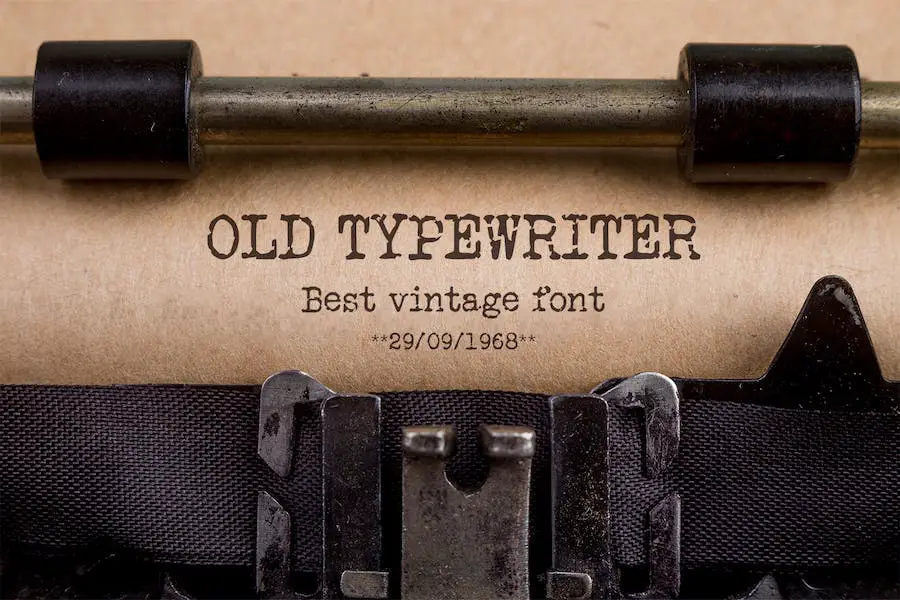
Old Typewriter هو خط آلة كاتبة يعيد سحر الكتابة الميكانيكية في تصميماتك. يضيف أسلوبها المصنوع من الألواح الرقيقة لمسة من الرجعية إلى إبداعاتك ، مما يجعلها مثالية لأولئك الذين يحبون المظهر الكلاسيكي.
هذا الخط متعدد الاستخدامات ويمكن استخدامه في مشاريع مختلفة مثل الصحف والملصقات والقمصان وفنون الجدران والمزيد.
بفضل تصميمها الموضوعي ، يمكن للآلة الكاتبة القديمة أن تجعل عناوينك بارزة وتضيف طابعًا إلى تخطيطات مجلاتك.
كما أن المظهر الفريد للخط يجعله اختيارًا ممتازًا لإنشاء تصميمات متعلقة بالطب الشرعي أو مسرح الجريمة. إنه خط من المؤكد أنه يجذب الانتباه ويجعل عملك متميزًا.
من خلال تصميمها الموضوعي ، تعد خطوط الآلة الكاتبة هي الأفضل للتصميم ويمكن أن تجعل عناوينك تنبثق وتضيف طابعًا إلى تخطيطات مجلاتك.
آلة كاتبة إنجما
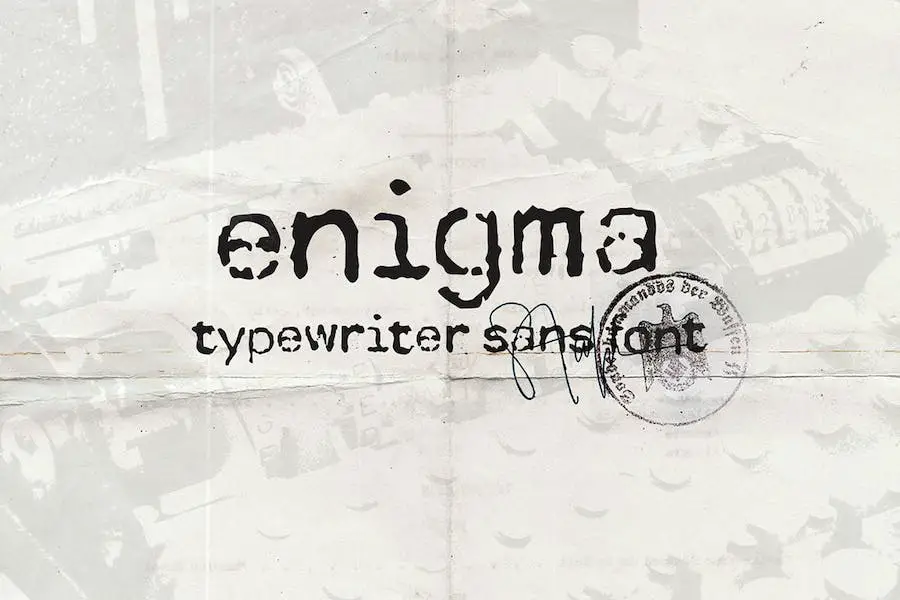
Enigma Typewriter هو خط يمكن أن يعيدك إلى الأيام الخوالي ، ويعيد إنشاء المستندات والأوراق القديمة بسهولة.
مستوحى من آلة Enigma German ، يأتي هذا الخط في ملف ttf واحد ، والذي يدعم الحروف الرسومية متعددة اللغات.
إذا كنت تبحث عن خط آلة كاتبة لإضافته إلى مشروع التصميم الخاص بك ، فقد يكون من المفيد التفكير في Enigma Typewriter.
بفضل طابعها العتيق ، يمكن أن تضفي على تصميمك طابع المدرسة القديمة الذي سيجذب انتباه الناس بالتأكيد. يعد Adobe Typewriter Font هذا مثاليًا للمصممين الذين يرغبون في تجربة أنماط طباعة مختلفة وإنشاء تصميمات فريدة.
كاتالينا آلة كاتبة
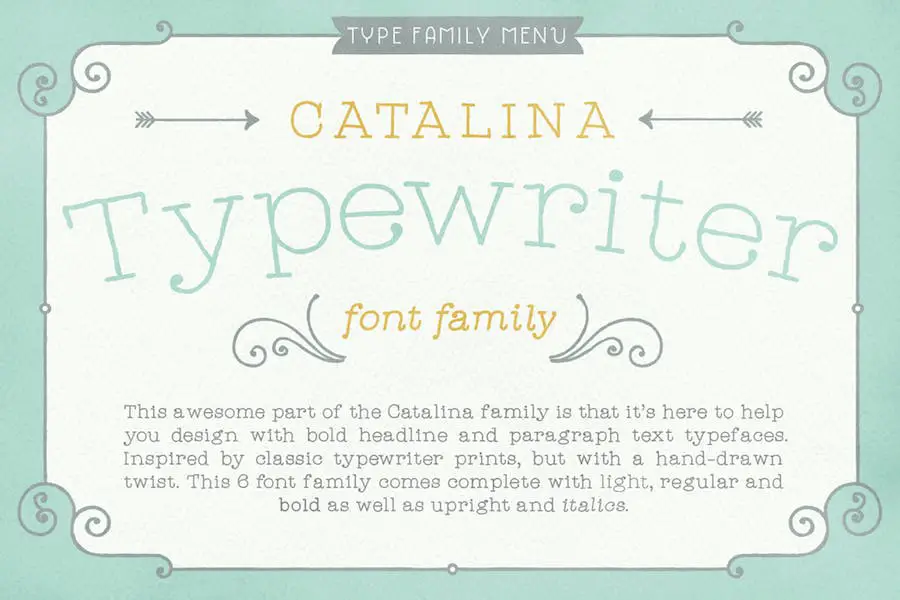
Catalina Typewriter هو خط يمكنه إضافة شخصية وشخصية لأي مشروع ، خاصة تلك المتعلقة بالموضوعات القديمة أو القديمة.
يأتي هذا الخط بثلاثة أوزان وأنماط مختلفة: sans و slab serif ، مما يمنح المصممين المزيد من الخيارات للاختيار من بينها.
لمصممي الجرافيك الذين يتطلعون إلى تحسين مشاريعهم على Canva ، يعد خط الآلة الكاتبة هذا خيارًا رائعًا لتحقيق مظهر بنمط الآلة الكاتبة.
وقع الآلة الكاتبة
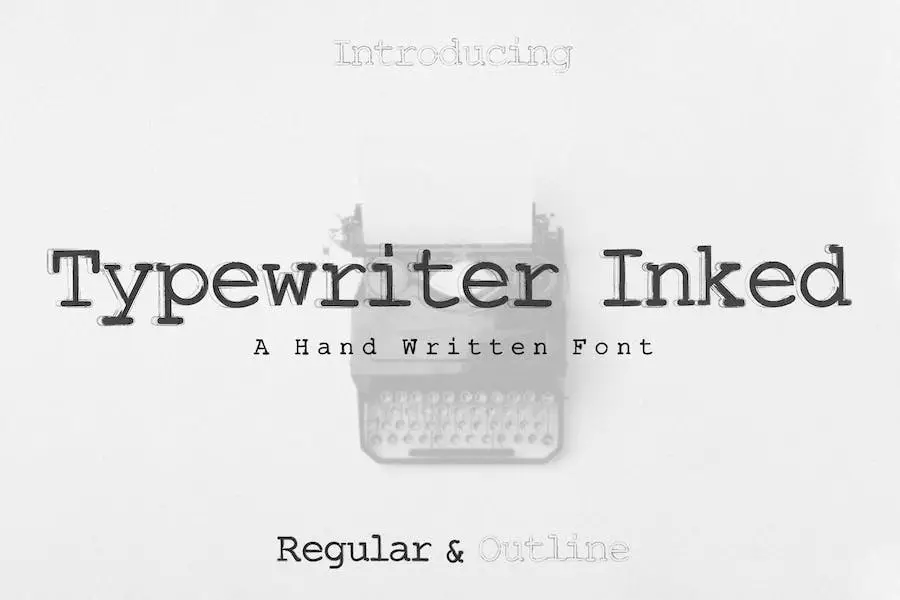
يعتبر الخط Typewriter Inked هو الخيار الأمثل لمصممي الجرافيك الذين يبحثون عن خط أنيق وفريد من نوعه للارتقاء بمشاريع التصميم الخاصة بهم.
يتألف هذا الخط من أحرف كبيرة وصغيرة وأرقام وعلامات ترقيم ورموز ، مما يجعله خيارًا متعدد الاستخدامات بشكل لا يصدق لاحتياجات التصميم المختلفة.
بأسلوبه الفاخر والواثق ، يعد هذا الخط مثاليًا لإنشاء تصميمات التغليف والعروض التقديمية والشعارات والعناوين الرئيسية والملصقات والعلامات التجارية والاقتباسات والعناوين وعناوين المجلات وتخطيطات الويب والإعلانات والدعوات وتصميم العبوات والكتب وأي تصميم إبداعي تقريبًا .
إذا كنت مصممًا يعمل على Figma ، فإن خط Typewriter Inked هو خيار ممتاز. بشخصياته الجريئة والقوية ، سيساعد هذا الخط تصميماتك على التميز ، مما يمنحها لمسة من الأناقة الكلاسيكية.
ريمنجتون الحرير
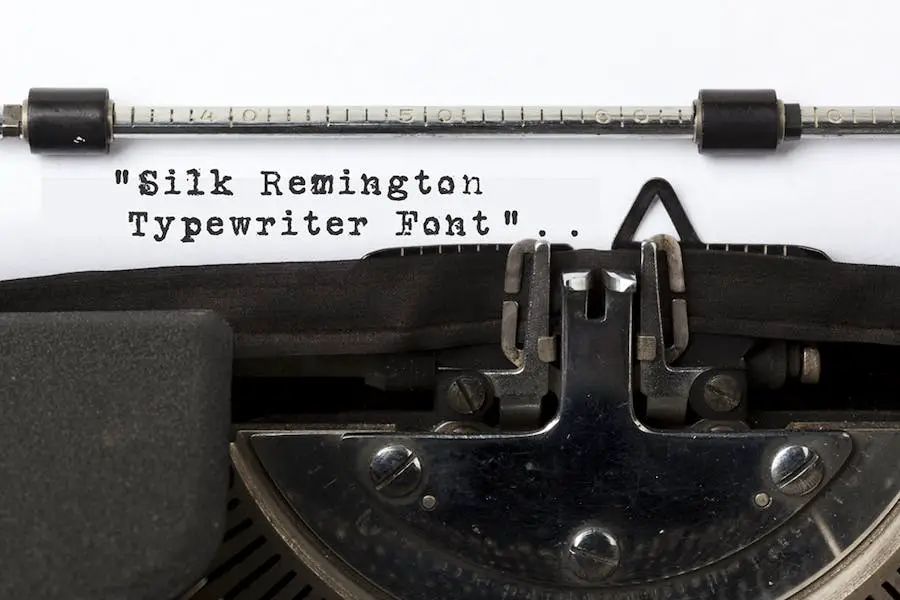
Silk Remington هو خط آلة كاتبة جديد تم تطويره بواسطة Jadugar Design Studio. تم تصميم خط الآلة الكاتبة الحديث هذا لتوفير إحساس واقعي بآلة كاتبة قديمة ، مما يمنح مشاريعك لمسة عتيقة.
يأتي Silk Remington في سبعة أنماط مختلفة ، بما في ذلك Thin و Regular و Rough Regular و SemiBold و Rough-SemiBold و Bold و Rough Bold.
كاتب
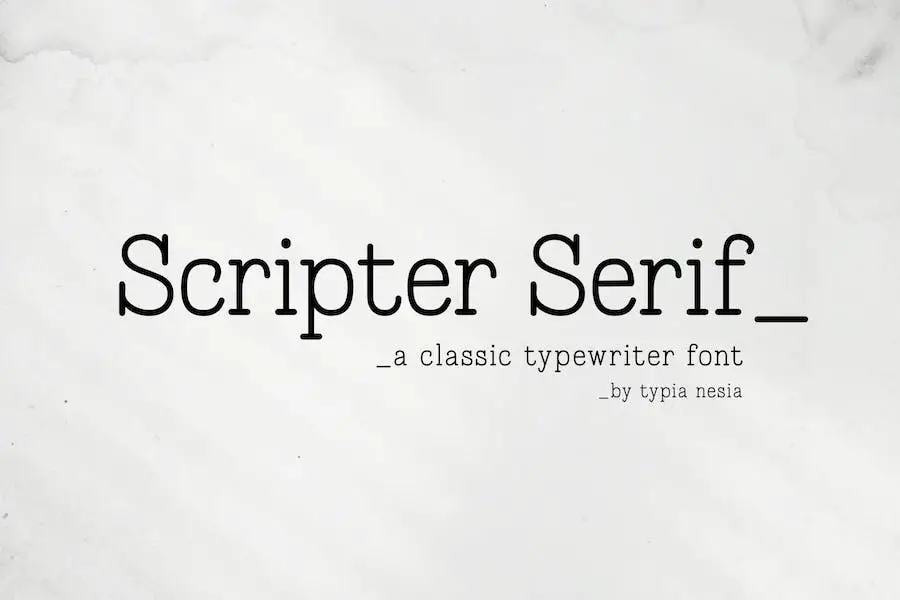
Scripter هو خط آلة كاتبة يمكن استخدامه في العديد من المشاريع ، من الشعارات الكلاسيكية والعلامات التجارية إلى تصميم المجلات. Scripter هو خط آلة كاتبة مثالي لأولئك الذين يرغبون في إضافة إحساس بالحنين إلى تصميماتهم.
يقدم هذا الخط تصميمًا تحريريًا كلاسيكيًا يناسب المواد الترويجية للأزياء والعلامة التجارية لمخطط الزفاف وتصميم القرطاسية. يعد Scripter أيضًا ممتازًا لتصميم المدونات وتصميم الإعلانات ودعوات بطاقات الزفاف والاقتباسات الفنية وديكور المنزل وعناوين غلاف الكتب / الروايات والمناسبات الخاصة.
ليس نوعي
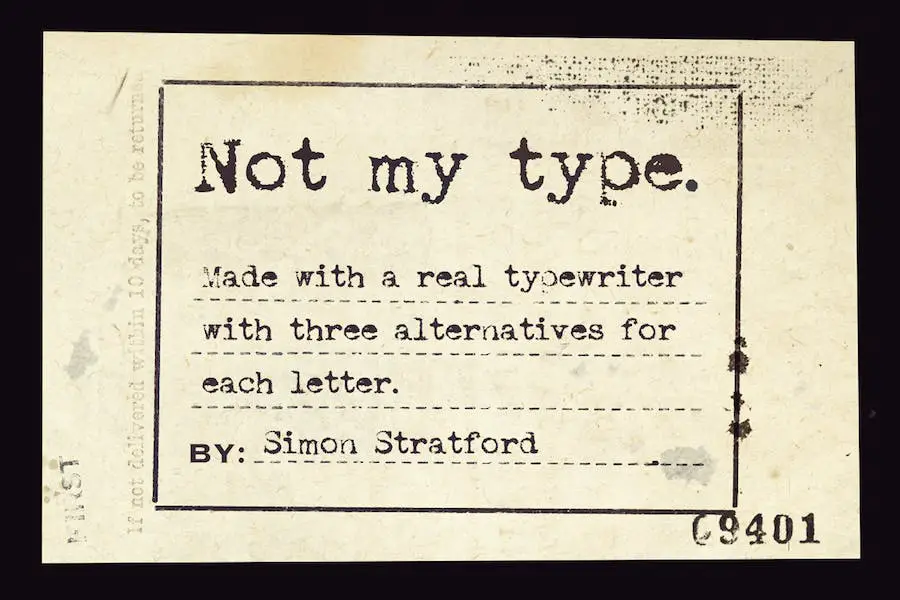
Not My Type هو خط يمكنه تحسين مشاريع التصميم الخاصة بك بمظهره الفريد والأنيق.
يأتي هذا الخط بنمط واحد يتضمن أحرفًا كبيرة وصغيرة ، إلى جانب ثلاثة بدائل لكل منها ، مما يوفر لك الكثير من الخيارات للاختيار من بينها.
ميرشانت ليدجر
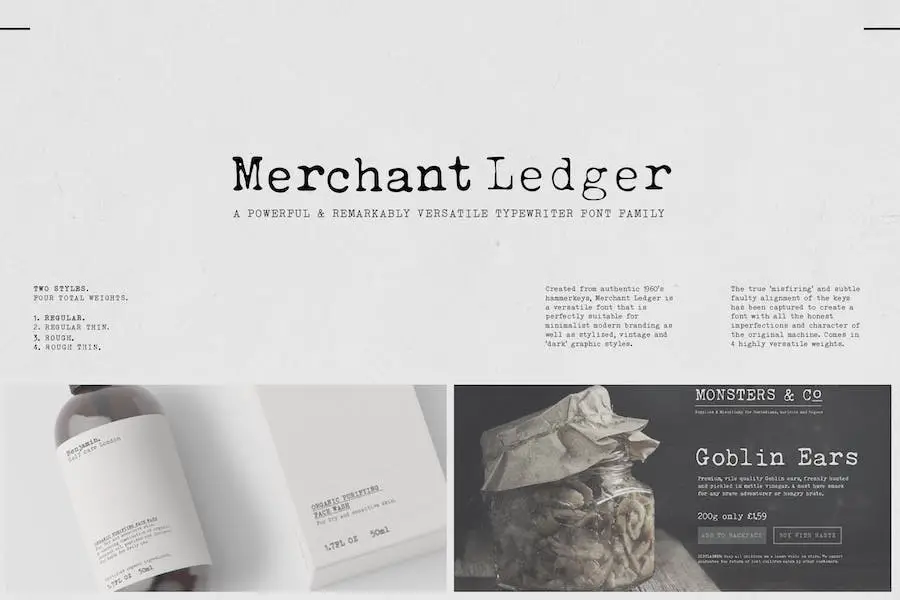
Merchant Ledger هي عائلة خطوط متعددة الاستخدامات بشكل لا يصدق يمكن استخدامها لمجموعة من التصميمات. سواء تم استخدامه للعلامات التجارية البسيطة والحديثة أو الملصقات الجريئة ، يمكن لخط الآلة الكاتبة هذا تقديم ما تحتاجه.
تايبريتر
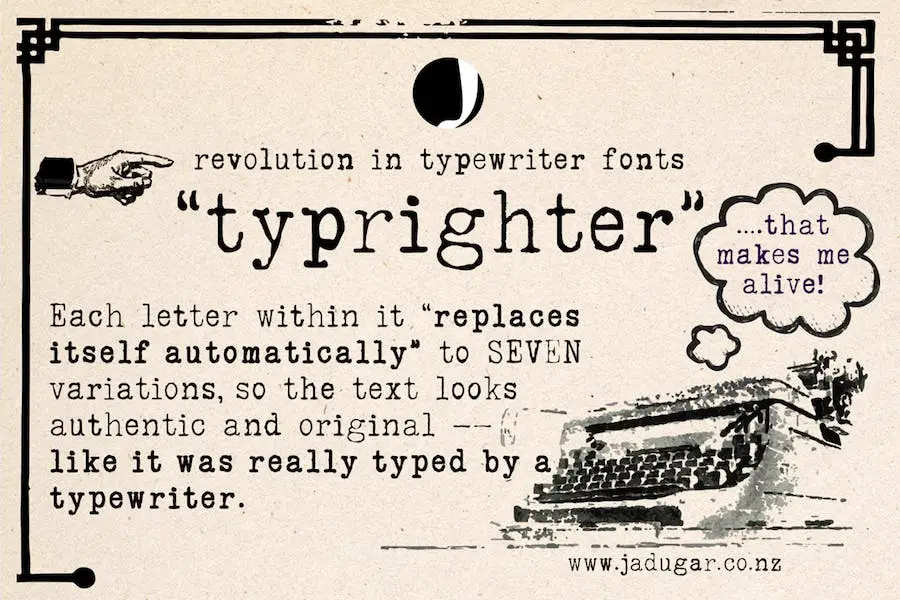
Typrighter هو خط يعد بجلب تجربة الآلة الكاتبة الحقيقية إلى جهاز الكمبيوتر الخاص بك. استخدم صانعو هذا الخط ميزة البدائل السياقية التطبيقية في Fontlab لإنشاء ستة أشكال مختلفة لكل حرف من الأبجدية الإنجليزية القياسية.
فوضى في Keytic
Mess in Keytic هو خط كلاسيكي مستوحى من جماليات حروف الآلة الكاتبة. يمكن استخدام هذا الخط لإنشاء فقرات أو نص ، بالإضافة إلى صياغة العناوين على أغلفة المجلات أو العناوين الرئيسية في الصحف.
رونس
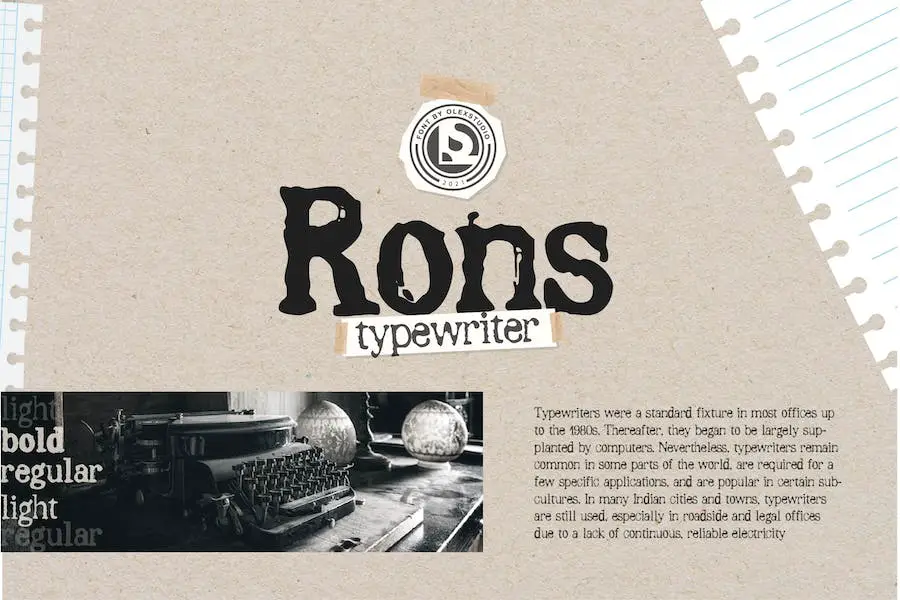
Rons Typewriter هو خط Serif مذهل يمكنه إضافة الأناقة والأناقة إلى جميع مشاريع التصميم الخاصة بك. يتميز هذا الخط الجميل بأحرف قياسية ، بما في ذلك الأحرف الصغيرة والكبيرة والأرقام وعلامات الترقيم والحروف الرسومية الدولية.
أفكار مثالية
أفكار مثالية هو خط آلة كاتبة رائع وممتع يأتي بثلاثة أشكال مختلفة. يتضمن الإصدار الأول علامات ختم أصلية مصنوعة بالحبر ، مما يوفر إحساسًا فريدًا وعتيقًا لتصميماتك.
الشكل الثاني له مظهر أكثر استقامة وخطورة ، مما يجعله مثاليًا للمشاريع الاحترافية. أخيرًا ، يتميز الخط الثالث بخط أساس غير منتظم ، مما يضيف لمسة غير تقليدية ومرحة إلى أي تصميم.
إعادة الكتابة
Retrotype هو خط مصمم لإضفاء القليل من الحنين إلى التصميم الحديث. إنه خط ممتع وكلاسيكي ومركب ومباشر يمكنه إضافة شخصية إلى أي مشروع. مستوحاة من الآلات الكاتبة الخالدة القديمة ، تم رقمنة Retrotype لعالم اليوم.
يأتي خط الآلة الكاتبة من Google مع العديد من الميزات التي تجعله متميزًا. إحدى السمات الجديرة بالملاحظة هي بساطته.
المحقق
Detective هو خط آلة كاتبة فريد يجمع بين سحر الطراز القديم وحساسيات العصر الحديث.
يشيد هذا الخط المصنوع يدويًا بالاختراع الكلاسيكي للآلة الكاتبة ، التي غيرت عادات القراءة وجعلت الوضوح في المقدمة.
باستخدام المحقق ، يمكنك إضافة لمسة شخصية قديمة إلى مراسلات عملك أو أي عمل آخر يتطلب مظهرًا رجعيًا.
يعد خط الآلة الكاتبة Detective خيارًا ممتازًا لمن يبحثون عن "Typewriter Fonts for Word".
آلة كاتبة
TYPEWRITER هو خط محرف عتيق مثالي لمصممي الجرافيك الذين يرغبون في إضافة لمسة من الحنين إلى مشاريعهم.
هذا الخط مستوحى من متاجر التحف والآلة الكاتبة القديمة ليسوع ، مما يجعله إضافة فريدة لمجموعة خطوط أي مصمم.
إذا كنت تبحث عن خط يمنح مشروعك طابعًا رجعيًا ، فإن TYPEWRITER يستحق بالتأكيد التفكير فيه.
بفضل الحروف المصممة بعناية والاهتمام بالتفاصيل ، فهي الخيار الأمثل لأي شخص يبحث عن خطوط الآلة الكاتبة لـ Circuit.
اكتب الكاتب القديم
يعد خط Type Old Writer خيارًا أنيقًا وفريدًا لمصممي الرسوم الذين يبحثون عن خط الآلة الكاتبة المثالي لرفع مشروعات التصميم الخاصة بهم.
يجسد هذا الخط ، بمظهره الكلاسيكي ، جوهر الكتابة القديمة بمظهرها المتميز والأصيل.
إحدى الميزات البارزة لـ Type Old Writer هي تنوعها. إنه يعمل بشكل جيد في مجموعة متنوعة من السياقات ، من تصميمات الطباعة مثل الملصقات والنشرات إلى التصميمات الرقمية مثل مواقع الويب وتطبيقات الأجهزة المحمولة.
بالإضافة إلى ذلك ، يمكنك استخدام خطوط الآلة الكاتبة لتصميمات الوشم ، مما يجعلها خيارًا رائعًا لأولئك الذين يتطلعون إلى إنشاء فن جسم مستوحى من الآلة الكاتبة.
خط الآلة الكاتبة
خط الآلة الكاتبة هو الخط المثالي للمصممين الذين يرغبون في تحقيق إحساس قديم وعتيق في تصميماتهم.
هذا الخط هو الأنسب للملصقات والمدونات والدعوات والبطاقات البريدية والعلامات التجارية والحروف بشكل عام. بمظهره الكلاسيكي والخالد ، من المؤكد أنه سيضيف لمسة من الحنين إلى أي مشروع.
يدعم هذا الخط اللغات اللاتينية الأساسية ، مما يجعله سهل الاستخدام عبر العديد من الأنظمة الأساسية. من السهل أيضًا قراءته وله نمط مميز يميزه عن الخطوط الأخرى.
يعتبر خط الآلة الكاتبة مثاليًا لإنشاء الشعارات أو تصميم مواقع الويب لأنه يمنح طابع المدرسة القديمة الذي يمكن أن يجعل مشروعك مميزًا.
سكرتير
يعد Secretary Typewriter خطًا كلاسيكيًا للآلة الكاتبة يأتي بوزن أخف وأخف وزنًا لمنح تصميماتك لمسة أكثر رقة. يعد هذا الخط مثاليًا لكل من النصوص الطويلة والقصيرة ، والصور المجمعة الرقمية ، والعلامات التجارية ، والتعبئة ، ومنشورات الوسائط الاجتماعية ، وأنماط الشعارات ، وغير ذلك الكثير.
واحدة من أفضل ميزات سكرتير الآلة الكاتبة هي تنوعها. يمكن استخدامه في تصميمات مختلفة ، من الطراز القديم إلى المعاصر ، وهو دائمًا مناسب تمامًا. بالإضافة إلى ذلك ، يضيف هذا الخط طابعًا فريدًا لأي تصميم يجعله متميزًا عن البقية.
بكرة الآلة الكاتبة
تم تصميم كل خط في Typewriter Spool بدقة مع الاهتمام بالتفاصيل ، مما يوفر مستوى لا مثيل له من الجودة والأصالة.
تشمل المجموعة مجموعة متنوعة من الأساليب ، من الأنماط البسيطة والبسيطة إلى الأكثر زخرفة وزخرفة ، مما يضمن وجود شيء يناسب كل الأذواق واحتياجات التصميم. سواء كنت تبحث عن طابع عتيق أو حافة معاصرة ، فإن الآلة الكاتبة Spool قد قمت بتغطيتها.
شعبية آلة كاتبة
Populaire Typewriter عبارة عن حزمة تصميم قديمة تقدم مجموعة من خطوط الآلة الكاتبة ، ومواد الورق ، وفرشاة ختم Photoshop.
تم الحصول على هذه المجموعة من مواد عتيقة حقيقية لإضفاء إحساس فريد وأصلي لأي مشروع تصميم يتطلب لمسة عتيقة.
الحزمة متعددة الاستخدامات ويمكن استخدامها في كل من المشاريع الرقمية والمطبوعة مثل النصوص الطويلة أو القصيرة ، والملصقات الرقمية ، والعلامات التجارية والتعبئة والتغليف ، ومنشورات الوسائط الاجتماعية ، والشعارات ، وغير ذلك الكثير.
آلة كاتبة مكتب
يعد خط Office Typewriter خيارًا ممتازًا لمصممي الجرافيك الذين يتطلعون إلى إضافة لمسة من السحر القديم إلى تصاميمهم. هذا الخط متعدد الاستخدامات ويمكن استخدامه في مجموعة واسعة من مشاريع التصميم الحديثة والكلاسيكية.
MachinaR
MachinaR هو خط يتميز بنظام دعم لغوي مثير للإعجاب. وهي تتميز بمجموعات أحرف أوروبا الغربية والوسطى والشرقية ، فضلاً عن اللغات البلطيقية والتركية.
بفضل مجموعة الأحرف الواسعة ، يعد MachinaR مثاليًا لمصممي الجرافيك الذين يرغبون في دمج لغات مختلفة في مشاريعهم دون القلق بشأن مشكلات التوافق.
آلة كاتبة غير متوقعة
الآلة الكاتبة غير المتوقعة هي خط يجلب المظهر الكلاسيكي لأحرف الآلة الكاتبة إلى مشاريع التصميم الخاصة بك. بفضل إلهامه المتجذر في التكنولوجيا القديمة ، يوفر هذا الخط أسلوبًا فريدًا وغير متوقع يمكن أن يعزز أي تصميم.
فلان الفلاني
JohnDoe هي عائلة خطوط فريدة تجمع بين أنماط الجرونج والآلة الكاتبة لإنشاء مظهر مميز لمشاريع التصميم الخاصة بك.
يأتي الخط بنمطين ، مما يضيف تنوعًا إلى نطاق استخداماته. تم نشر JohnDoe من قبل Fonthead Design Inc. ، وتم إنشاؤه من عينة آلة كاتبة حقيقية ، مما يوفر إحساسًا كلاسيكيًا أصيلًا.
أفضل خطوط خالية من الآلة الكاتبة
إذا كنت مصممًا جرافيكًا تتطلع إلى إضافة لمسة من الذوق الكلاسيكي إلى تصميماتك ، فلا تنظر إلى أبعد من قائمتنا المنسقة لأفضل الخطوط المجانية للآلة الكاتبة. قم بالتمرير واكتشف بعض الجواهر الخفية التي من المؤكد أنها سترتقي بمشروعك القادم.
الآلة الكاتبة الشريرة
يعد خط Evil Typewriter خيارًا مثاليًا لأولئك الذين يبحثون عن خط جرونج مرعب ومخيف لإضفاء الإثارة على مشاريعهم التي تحمل طابع الهالوين.
كما يوحي الاسم ، فإن خط Evil Typewriter يعطي رعبًا وجوًا مخيفًا يناسب جيدًا ملصقات أفلام الرعب وأغلفة الكتب والنشرات وأي مشاريع أخرى ذات صلة.
عم آلة كاتبة
Uncle Typewriter by Typo 5 هو خط TTF مجاني يمكن استخدامه على كل من MAC والكمبيوتر الشخصي. هذا الخط مثالي لأولئك الذين يبحثون عن أسلوب آلة كاتبة عتيق لإضافته إلى تصميماتهم. تشتمل مجموعة الأحرف على أحرف أبجدية صغيرة وكبيرة بالإضافة إلى أرقام.
KG الهولوسين
KG Holocene هو خط آلة كاتبة غريب الأطوار يضيف لمسة من المرح إلى أي مشروع. تم إنشاؤه بواسطة Kimberly Geswein ، وهو مجاني للاستخدام الشخصي ومثالي لإضافة لمسة فريدة إلى تصميماتك.
آلة كاتبة توكس
Tox Typewriter هو خط تبرعات تم إنشاؤه بواسطة junkohanhero يمكنه إضافة لمسة فريدة إلى تصميماتك. يوفر هذا الخط المستوحى من الآلة الكاتبة إحساسًا قديمًا ورجعيًا من شأنه ترقية مظهر مشاريعك.
وقع الآلة الكاتبة
الآلة الكاتبة Inked هي خط عتيق يضيف طابعًا إلى أي مشروع تصميم. تمنحه الأحرف ذات نمط الحبر إحساسًا أصيلًا مثاليًا للشعارات والعلامات التجارية والمواد المطبوعة.
مع كل من الأحرف الكبيرة والصغيرة ، تتميز الآلة الكاتبة Inked بالتنوع لاستخدامها في التطبيقات المختلفة. يوفر أسلوبه الرقيق البنية والأناقة ، بينما يمنحه تأثير الحبر القديم طابعًا فريدًا يميزه عن الخطوط الأخرى.
آلة كاتبة خشنة
Rough Typewriter هو خط تم إنشاؤه بواسطة JibbaJabba Fonts وهو مثالي لإضافة مظهر كلاسيكي إلى تصميماتك. هذا الخط مجاني للاستخدام الشخصي ويتضمن 125 حرفًا و 318 حرفًا.
مع نسيجها الخام وأسلوب الآلة الكاتبة للمدرسة القديمة ، فإن Rough Typewriter هو الخط المثالي للمصممين الذين يتطلعون إلى إضافة لمسة من الحنين إلى مشاريعهم. يتميز هذا الخط بمسافة غير منتظمة ، مما يضيف إلى سحره الريفي ، مما يجعله مثاليًا لإنشاء الملصقات والنشرات وحتى أغلفة الكتب.
تألق الآلة الكاتبة
Shine Typewriter هو خط ممتع وغريب سيضيف لمسة فريدة إلى مشاريع التصميم الخاصة بك. يجلب خط الآلة الكاتبة المصنوع يدويًا أسلوبًا رجعيًا وجنائيًا إلى أي مشروع تعمل عليه. يشتمل الخط على أحرف كبيرة وصغيرة ، بالإضافة إلى أرقام وعلامات ترقيم ورموز.
X آلة كاتبة
X Typewriter هو خط مجاني صممه GGBotNet يحاكي المظهر الكلاسيكي للآلة الكاتبة. يُعد هذا الخط مثاليًا لمصممي الجرافيك الذين يسعون إلى إضافة لمسة من الحنين والأصالة إلى تصميماتهم ، مما يضفي طابع المدرسة القديمة على أي مشروع.
كاتب تيرتو
Tirto Writer هو خط مصمم لاستحضار حنين الآلات الكاتبة القديمة. تتضمن حزمة الخطوط المرخصة هذه أحرفًا كبيرة وصغيرة ، بالإضافة إلى علامات الترقيم والأرقام.
تجعله الجمالية القديمة للخط اختيارًا ممتازًا للمصممين الذين يرغبون في إضافة لمسة من السحر القديم إلى مشاريعهم. إنها خطوط نظيفة وتصميم بسيط يجعلها متعددة الاستخدامات بما يكفي للعمل في مجموعة متنوعة من السياقات.
الآلة الكاتبة أمي
Mom's Typewriter هو خط مذهل ومثالي لمصممي الجرافيك الذين يرغبون في إضافة طابع كلاسيكي إلى تصاميمهم. تم إنشاء هذا الخط بواسطة Christoph Mueller وهو متاح مجانًا ، مما يجعله خيارًا ممتازًا للمصممين المهتمين بالميزانية.
الرحلة مرفوضة
Trip Denied هو خط Billy Argel مثالي للاستخدام الشخصي. يعد هذا الخط اختيارًا ممتازًا لتحسين تصميم مشاريعك ، خاصةً إذا كنت تبحث عن خط بنمط الآلة الكاتبة.
واحدة من أفضل ميزات Trip Denied هي مظهرها الفريد من نوعه على الآلة الكاتبة. يتميز بإحساس عتيق وملمس خشن قليلاً يجعله متميزًا عن الخطوط الأخرى. بالإضافة إلى ذلك ، من السهل جدًا قراءتها ، مما يجعلها خيارًا مثاليًا للعناوين أو العناوين.
الآلة الكاتبة الحديثة
Modern Typewriter عبارة عن مجموعة مجانية من خطوط الآلة الكاتبة الحديثة التي أنشأها Lukas Krakora. هذه الخطوط مناسبة لأي شخص يتطلع إلى إضافة طابع قديم أو قديم إلى مشاريعه أو مستنداته أو تصميماته.
تتضمن مجموعة الخطوط هذه مجموعة متنوعة من الأنماط ، مثل الآلات الكاتبة Cella الألمانية الشرقية من الثمانينيات ، ونمط الإيصال ، والخطوط الحديثة جدًا. سواء كنت بحاجة إلى خط لاستخدامه في مشروع يتطلب مظهر آلة كاتبة أصليًا أو تصميمًا يحتاج إلى لمسة من الحنين إلى الماضي ، فإن Modern Typewriter قد قمت بتغطيته.
التعليمات
تم تصميم خطوط الآلة الكاتبة في الأصل للاستخدام على الآلات الكاتبة الميكانيكية في أواخر القرن التاسع عشر. استخدمت الآلات الكاتبة الأقدم خطوطًا ذات عرض ثابت ، مما يعني أن كل حرف شغل نفس القدر من المساحة.
بمرور الوقت ، بدأ المصممون في تجربة أشكال مختلفة من الخطوط ، مما أدى إلى إنشاء العديد من خطوط الآلة الكاتبة الشهيرة التي نعرفها اليوم. اليوم ، لا تزال هذه الخطوط مشهورة لسحرها القديم وجاذبيتها الخالدة.
يمكن أن تضيف خطوط الآلة الكاتبة لمسة فريدة وحنين إلى أي مشروع تصميم. تم تصميم هذه الخطوط في الأصل للاستخدام على الآلات الكاتبة ، مما يمنحها مظهرًا خالدًا ومثاليًا لإضافة شخصية إلى عملك. إنها أيضًا رائعة لإنشاء تصميمات قديمة أو مستوحاة من الطراز القديم.
خاتمة
في الختام ، اكتشفنا 36 من أفضل خطوط الآلة الكاتبة لمصممي الجرافيك لاستخدامها في مشاريعهم. توفر هذه الخطوط إحساسًا قديمًا ورجعيًا يمكن أن يضيف طابعًا وسحرًا إلى أي تصميم. من أنماط serif الكلاسيكية إلى أنماط sans-serif الحديثة ، يوجد خط لكل مشروع وجمالي.